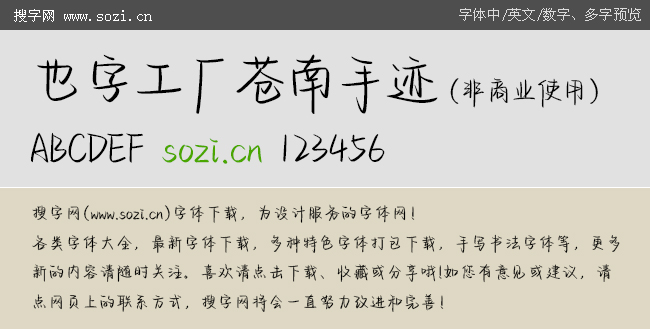
也字工廠蒼南手跡
搜字網(wǎng)給大家提供一款也字工廠蒼南手跡(非商業(yè)使用)中文字體下載,也字工廠蒼南手跡是一款手寫書法字體,字體書寫流暢自然,字形瀟灑大方。具有很好的視覺效果。適合應(yīng)用于藝術(shù)設(shè)計、平面宣傳設(shè)計、網(wǎng)頁設(shè)計、海報設(shè)計等應(yīng)用(此字體為個人非商用版,商用可以聯(lián)系:官方網(wǎng)址:https://yefont.com/home,聯(lián)系方式:13798980448)。